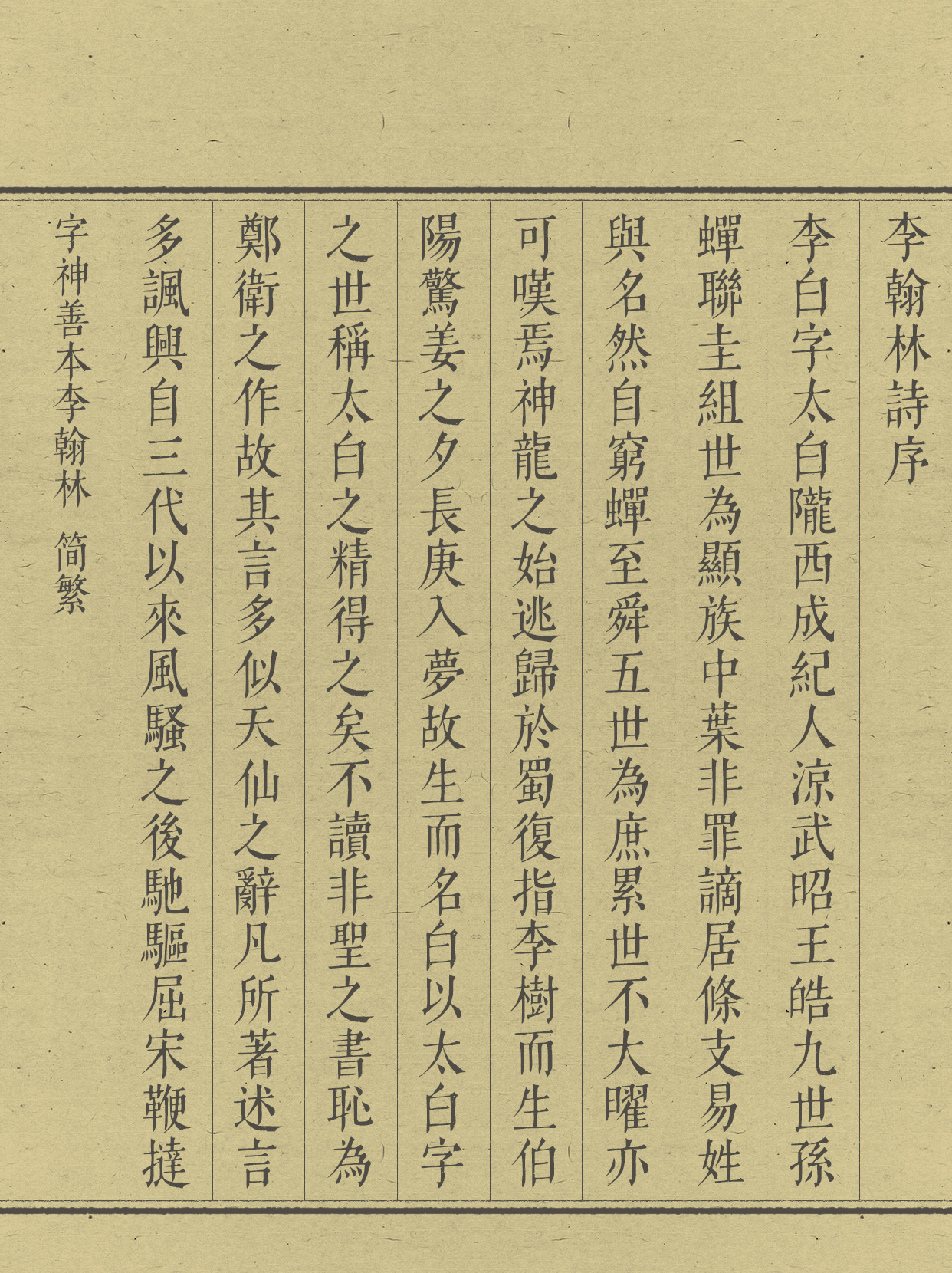
字神善本李翰林 简繁
明万历四十年(1612)刘世教刊《李翰林全集》四十二卷,以源自嘉靖、万历间主流成熟的 “明体”坊刻风格为基底,兼具规范与文人意趣,整体呈现 “精整秀雅、体式统一” 的美学特质,是明代白文本李白集的代表性刻本之一。将此中的古典宋刻本匠心与诗仙的浪漫文化气质延续传承到数字化的字体中, 在现代的平面设计作品中呈现出飘逸豪健且兼具诗意的视觉特质。适合应用于古典文化宣传、诗词集封面、书法艺术展览、历史主题海报等场景。